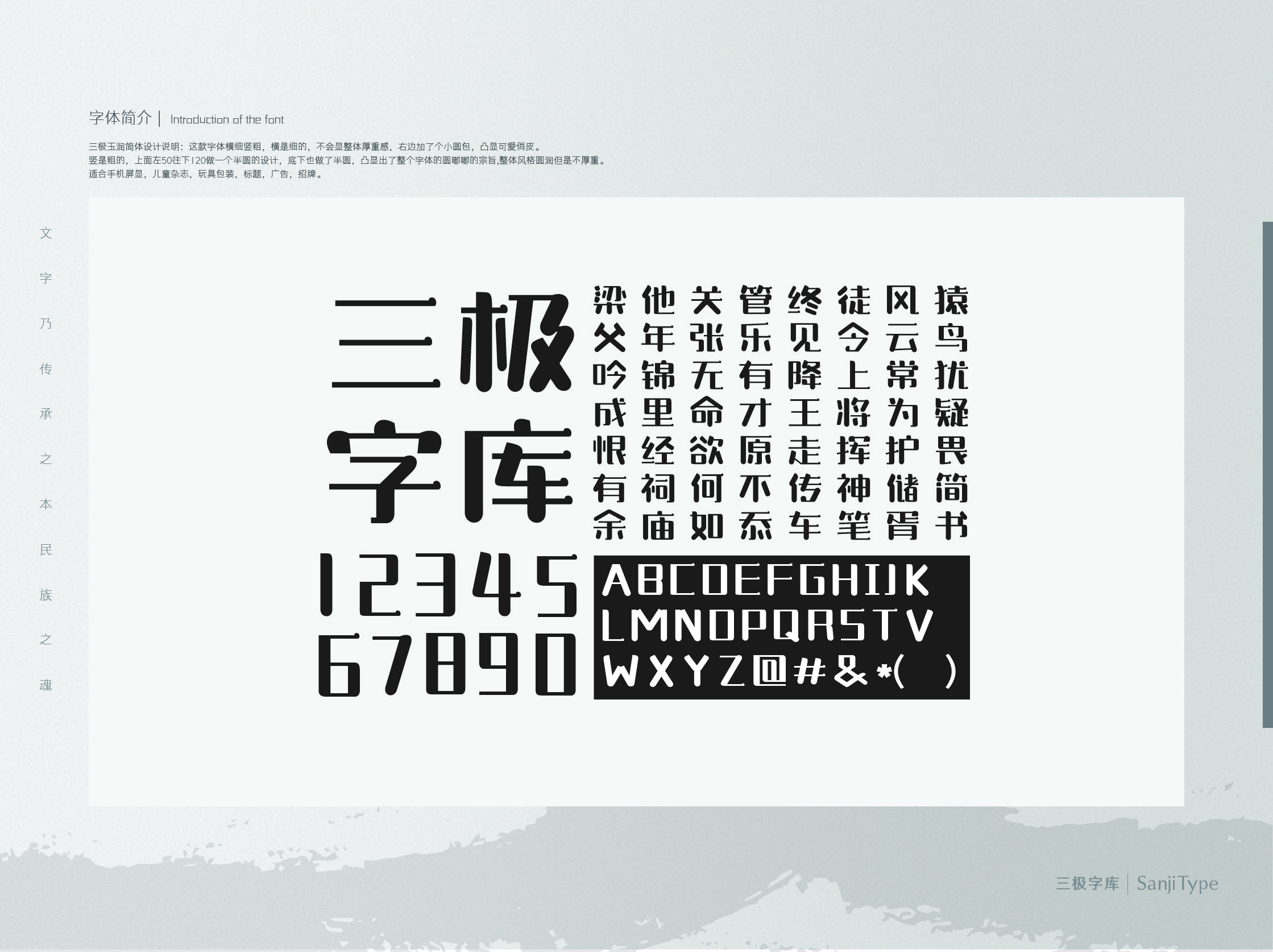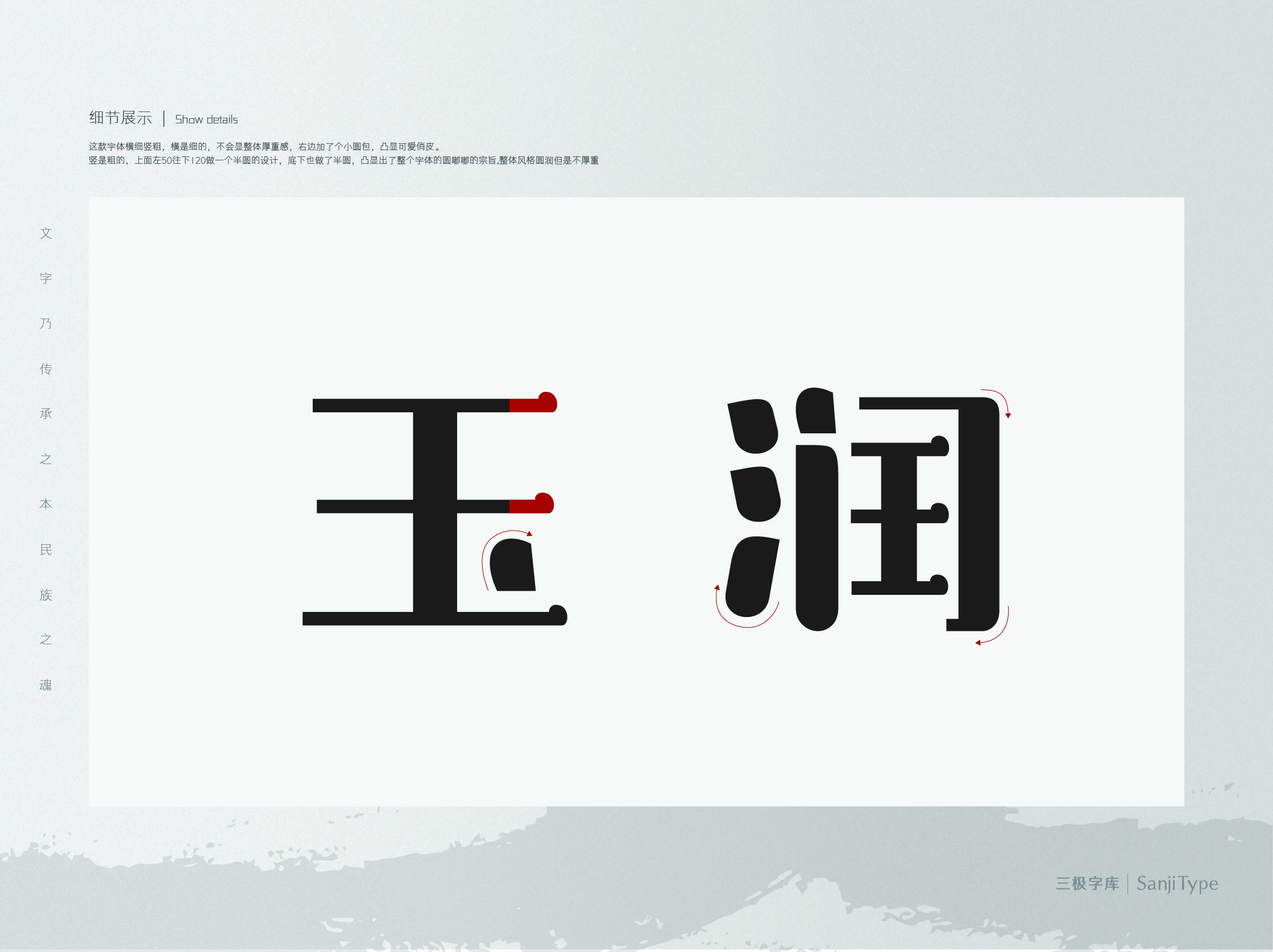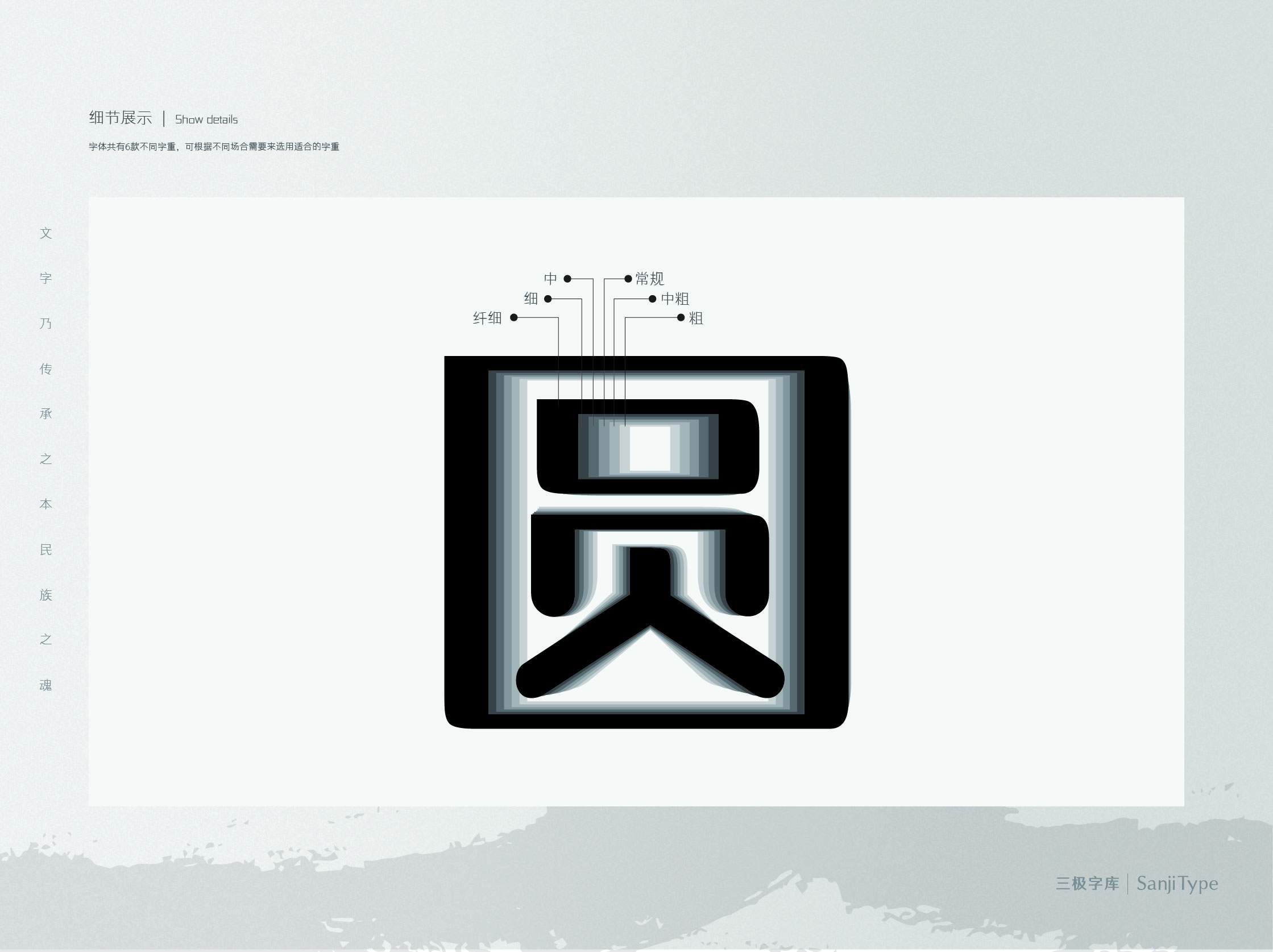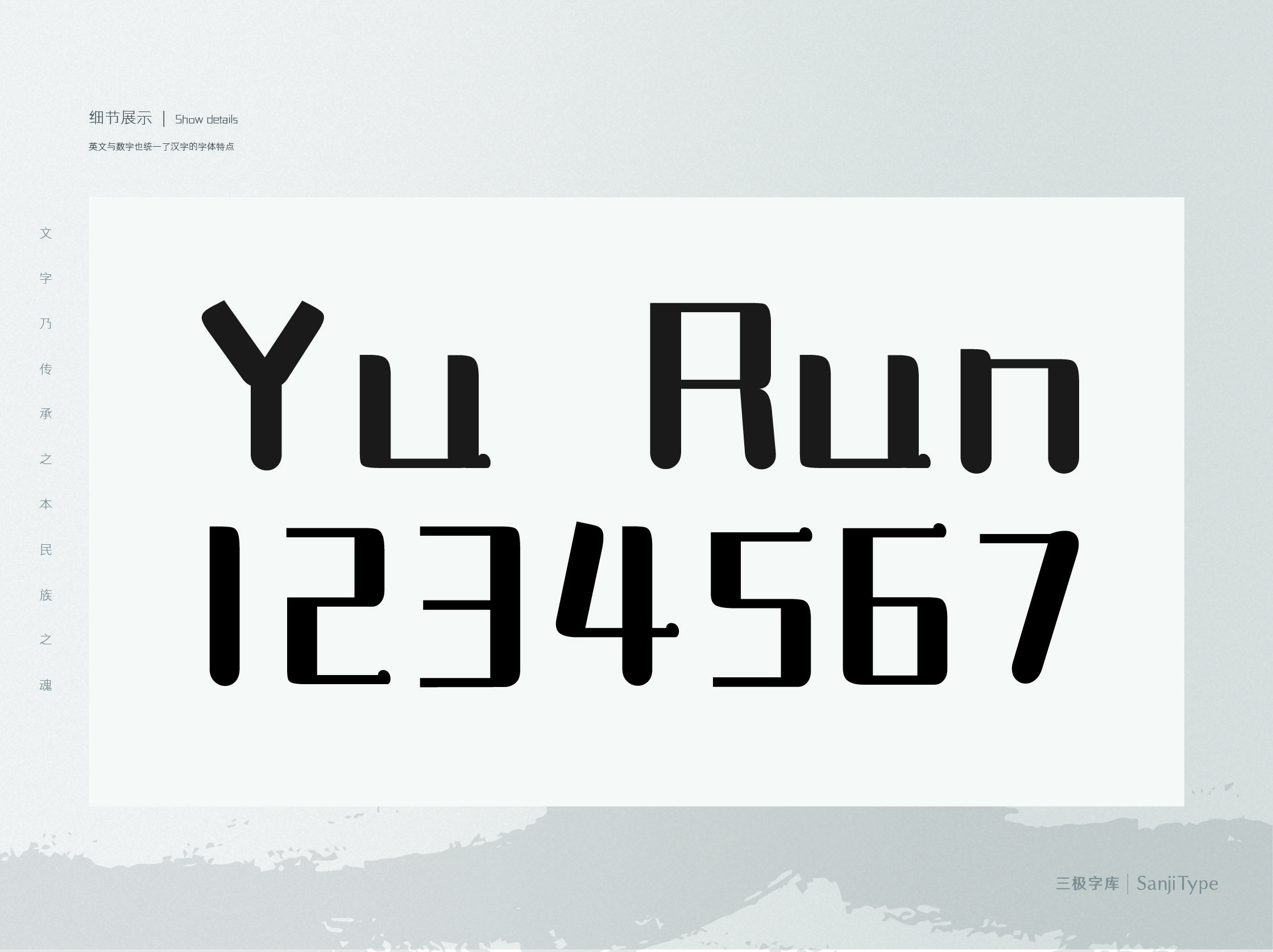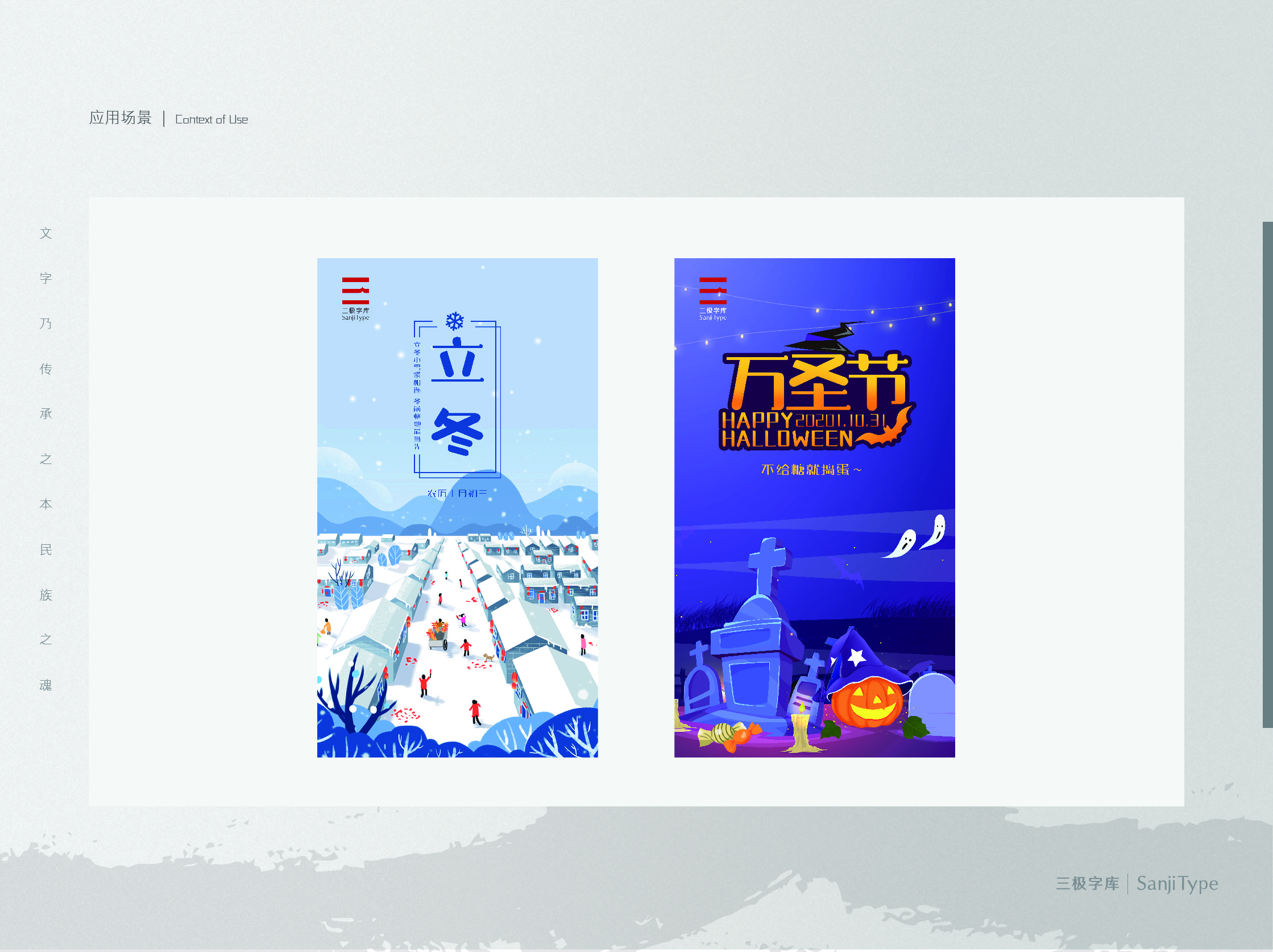
三极玉润简体家族
罗碧霞 庞丽珊 朱文淑
三极玉润简体系列:这款字体横细竖粗,对比强烈。纤细的横笔,减弱了字体的灰度,增强呼吸感,不会显得厚重,横笔右端加了个小圆包,凸显可爱俏皮。粗壮的竖笔,顶部右端转成圆角端点,底部也做了半圆,遵循整体圆嘟嘟的宗旨。这款字的宝盖头也是圆润饱满的,和点相呼应,整体风格圆润但是不厚重。适合手机屏显,儿童杂志,玩具包装,标题,广告,招牌。